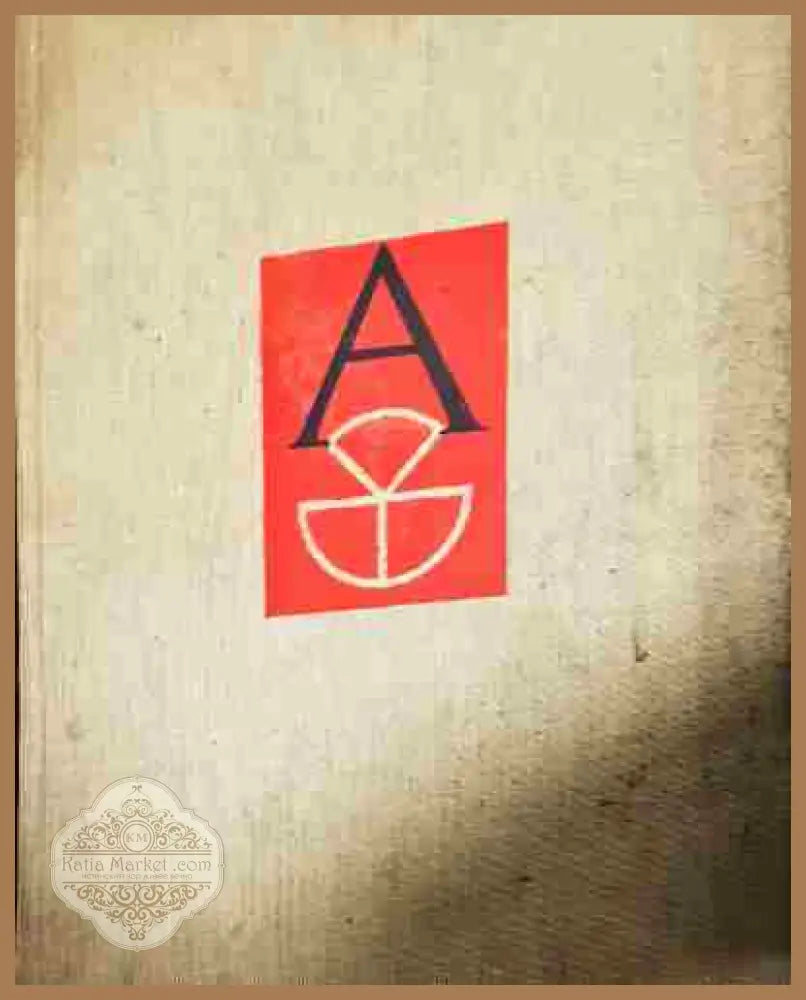
Древен и съвременен български шрифт - Васил Йончев, Олга Йончева
Древен и съвременен български шрифт е задълбочено изследване на историята и практиката на българската типография, създадено от Васил Йончев и Олга Йончева. Това издание от Антикварен магазин - Катя Маркет съчетава академично разбиране с богат експонат за дизайнери, колекционери и преподаватели, търсещи корените на кирилицата и нейните модерни приложения.
• Автори: Васил Йончев, Олга Йончева – водещи фигури в българската типография, с дълбоки знания за историческите форми и съвременните техники за тяхното използване.
• Уникална стойност: Свързва древните образци на българските букви с модерните практики в дизайн и печат, показвайки как контекстът оформя изборите в лейаут и идентичност.
Ползи за читателя: Това издание ви помага да разберете еволюцията на българската кирилица и нейните отразени форми в съвременните шрифтови решения. За дизайнерите и студентите е ценен източник за основи на типография, както и за конкретни насоки при разработката на лейаут, редакционни материали и бранд идентичности. За колекционери и библиотеки книгата представлява атрактивен експонат с историческо значение и висока стойност, поддържана от качеството на твърдата подвързия и запазената книга от 1982 година. Изданието е част от портфолиото на Антикварен магазин - Катя Маркет, носещ доверие в автентичността и грижата за запазената книжнина.